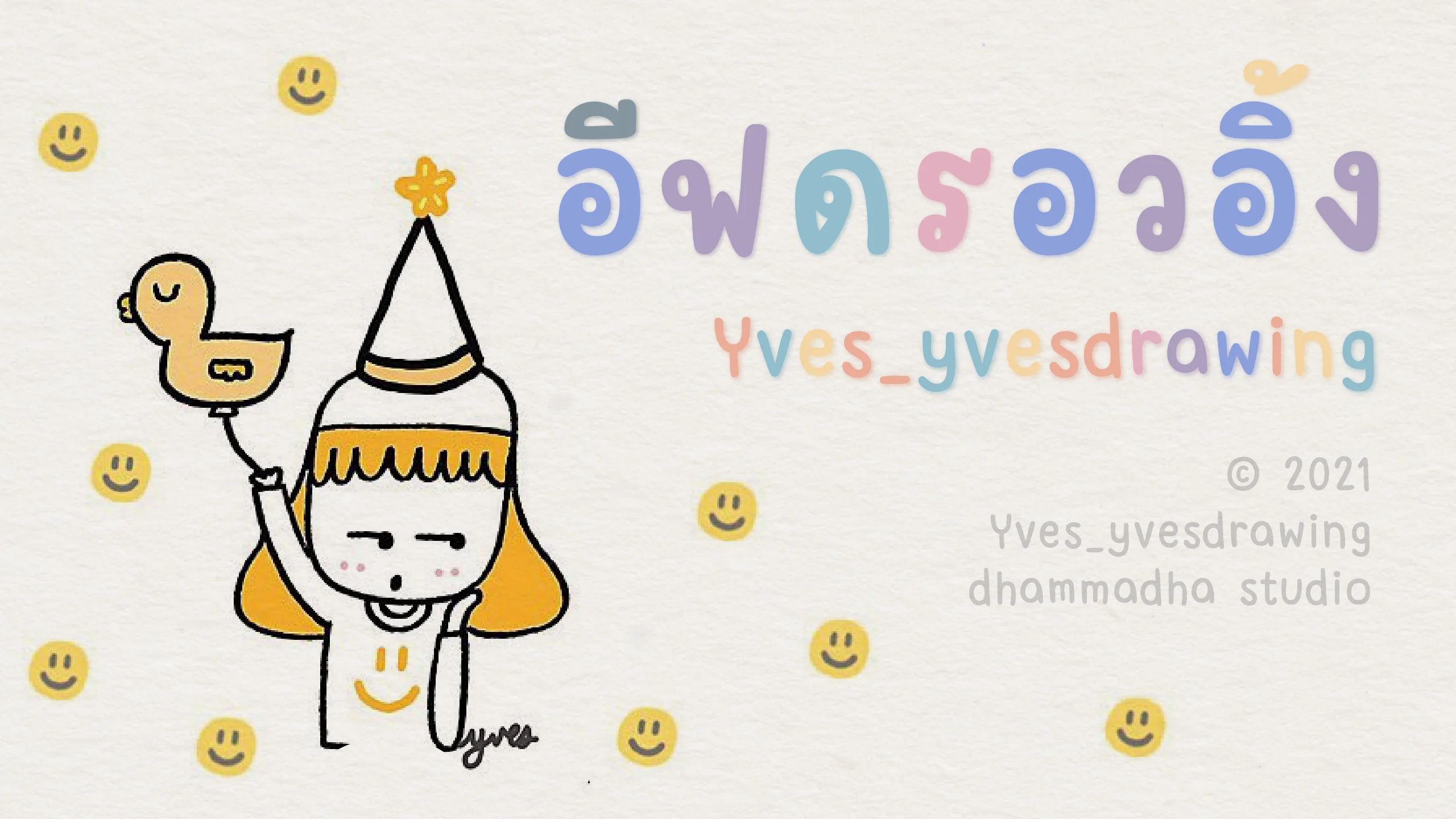
Yves_yvesdrawing
ชุดอักษรที่ถ่ายทอดลายเส้นสุดน่ารักจากเพจ Yves_yvesdrawing ซึ่งผ่านกระบวนการคัดสรรและพัฒนาอย่างประณีตมาอย่างยาวนาน เพื่อเปลี่ยนลายมือที่มีเสน่ห์เฉพาะตัวให้กลายเป็นฟอนต์ที่ใช้งานได้อย่างสมบูรณ์แบบ ฟอนต์ชุดนี้โดดเด่นด้วยคาแรคเตอร์ที่ดูขี้เล่นและมีความเป็นธรรมชาติสูง เหมาะอย่างยิ่งสำหรับใช้เป็นฟอนต์พาดหัว (Display Font) ที่ต้องการความสะดุดตาและดูมีเอกลักษณ์ หรือจะใช้จัดวางเป็นเนื้อความ (Text Font) ขนาดสั้นๆ เพื่อเพิ่มความเป็นกันเองและสร้างบรรยากาศที่อบอุ่นให้กับงานออกแบบของคุณ ด้วยความตั้งใจที่อยากมอบประสบการณ์การสร้างสรรค์ที่สนุกสนานยิ่งขึ้น "อีฟดรอวอิ้ง | Yves_yvesdrawing" จึงเป็นมากกว่าแค่ตัวอักษร แต่เป็นเครื่องมือที่จะช่วยเติมเต็มจินตนาการและทำให้ทุกชิ้นงานของคุณดูมีชีวิตชีวา มอบความสะดวกสบายและประหยัดเวลาในการออกแบบได้อย่างเหลือเชื่อ เพื่อให้ผลงานของคุณดูน่ารักโดดเด่นกว่าที่เคย พิเศษ !! สำหรับทุกการสั่งซื้อชุด FAMILY แถมฟรี Yves_yvespainting (Color Font) อีก 4 ฟอนต์ (รวมทั้งสิ้น 8 ฟอนต์) ฟอนต์ลงสีสำเร็จ พิมพ์ปุ๊บ พร้อมใช้ปั๊บ เชื่อสิ..ว่าสนุก !! * ฟอนต์สีสามารถใช้งานได้กับโปรแกรมที่รองรับเท่านั้น ออกแบบโดย : Yves Nimpanich พัฒนาฟอนต์โดย : Montonn Thanaroj